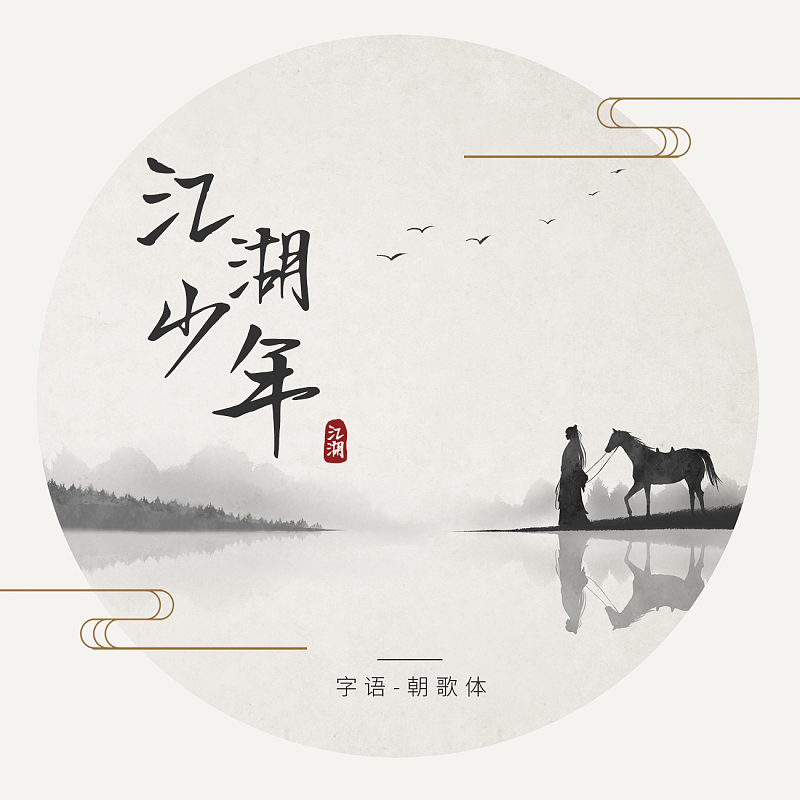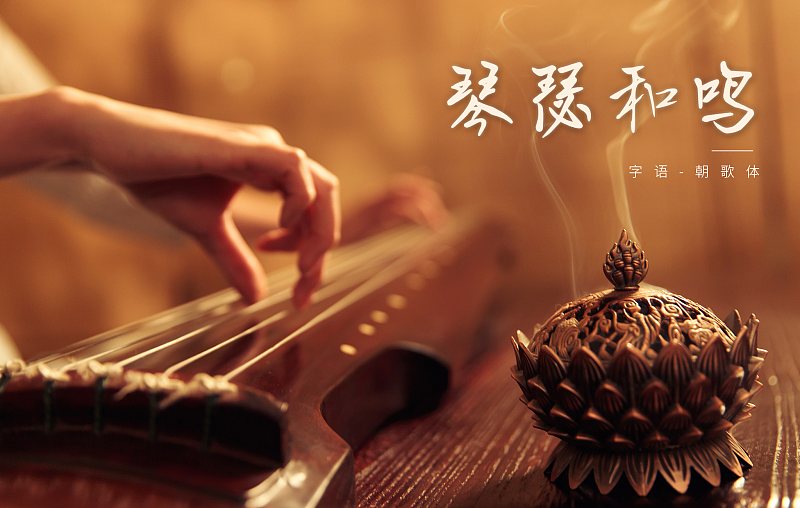
字語(yǔ)朝歌體
朝歌體這款字體筆畫(huà)鋒利尖銳,行筆勁健爽利、灑脫飄逸、具有很強(qiáng)的視覺(jué)沖擊,給人一種俠客的感覺(jué),整體瀟灑硬朗。適用于文藝類的書(shū)刊,品牌廣告和產(chǎn)品包裝設(shè)計(jì),以及社交網(wǎng)絡(luò)的個(gè)性化用字。